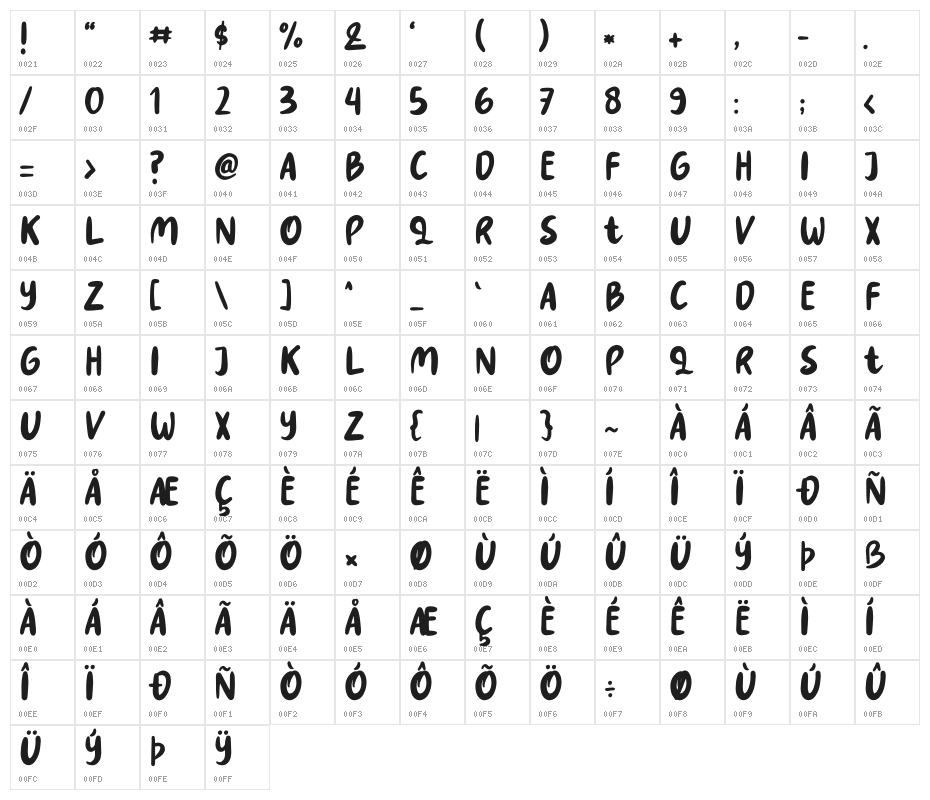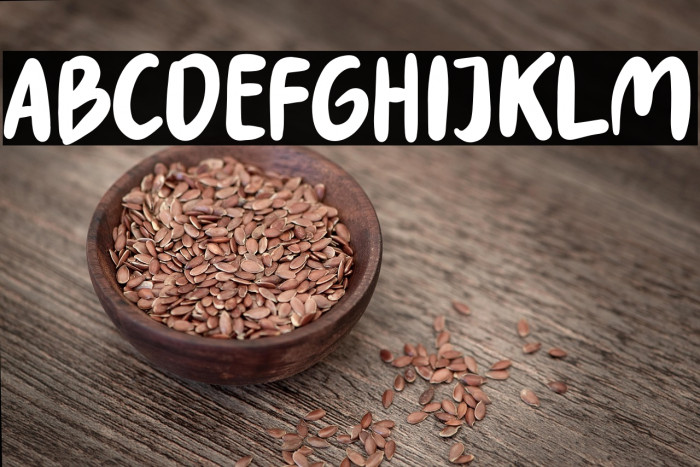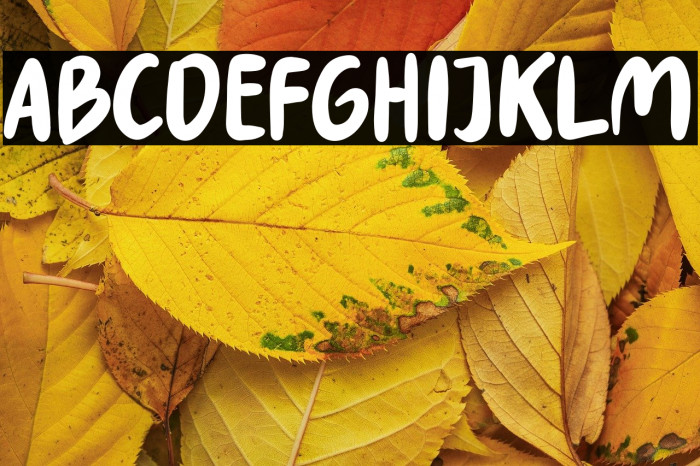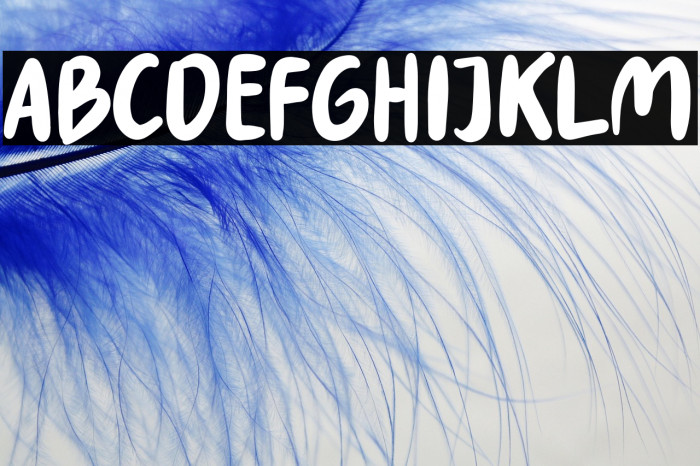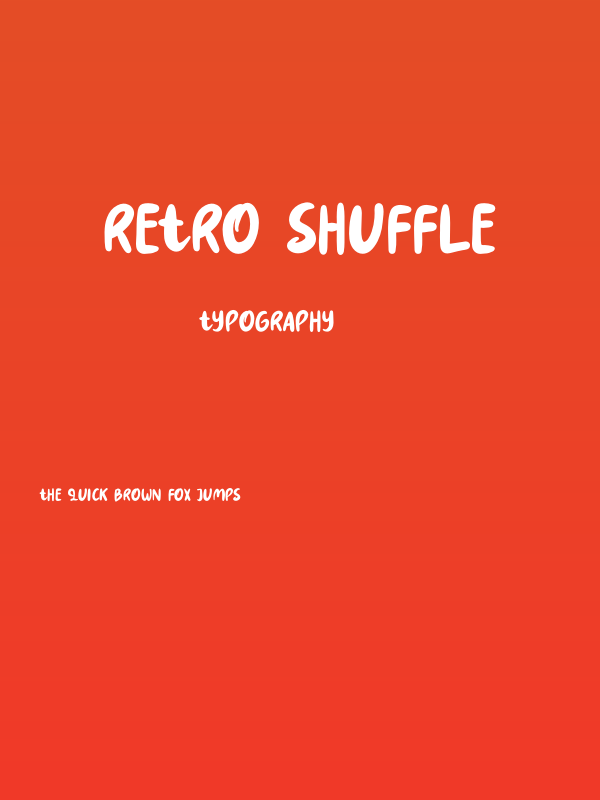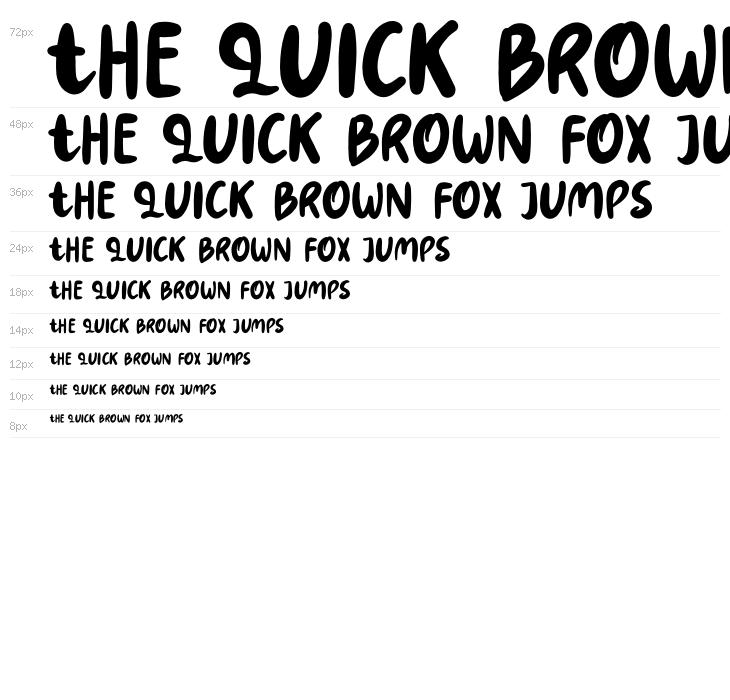
Retro Shuffle Font
| Gesamtstil | Retro, Playful |
| Vorgeschlagene Projekte | Ideal for posters, children's books, playful branding, and creative social media graphics. |